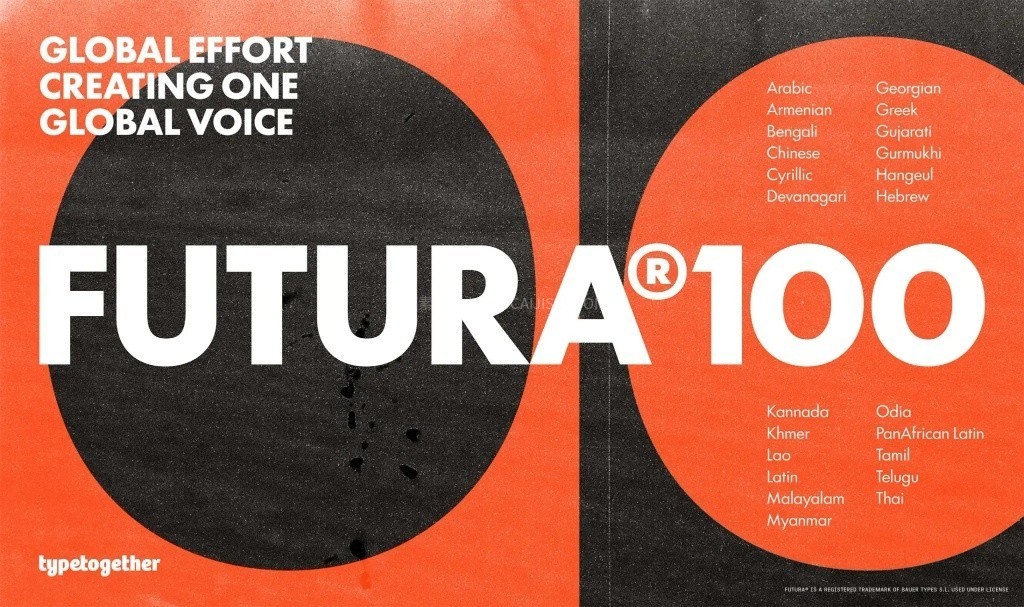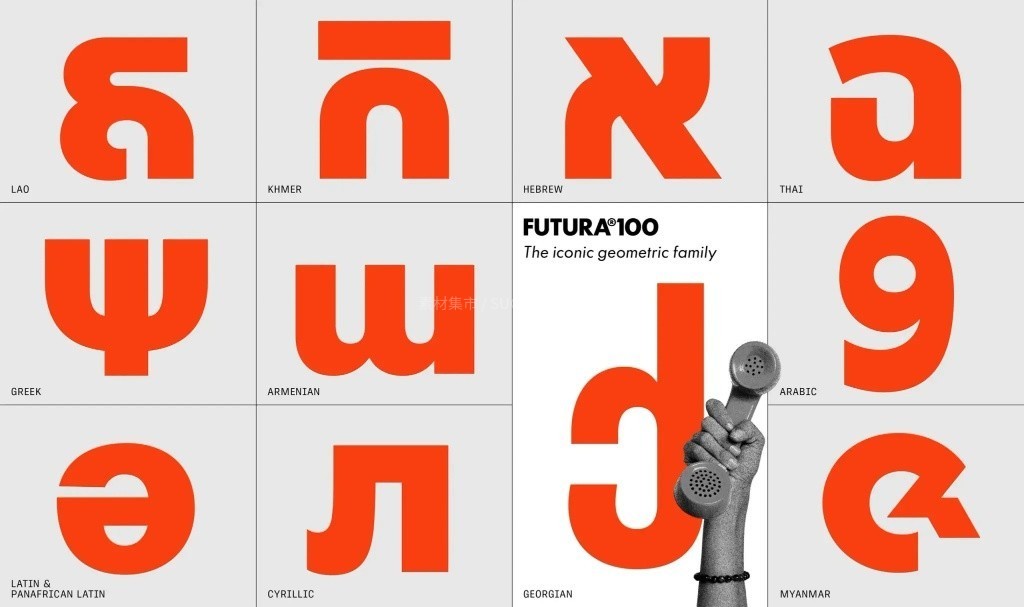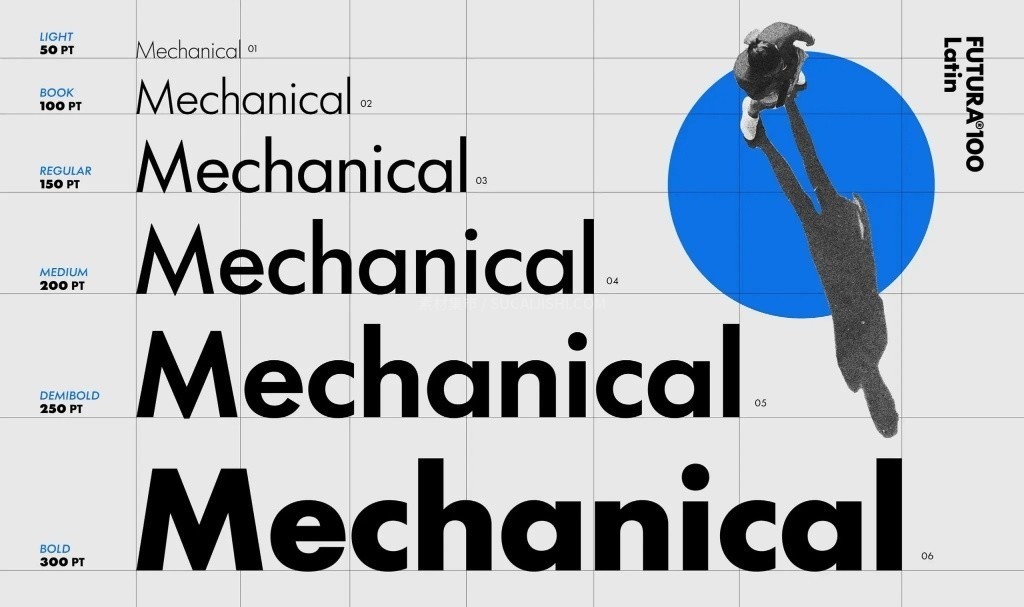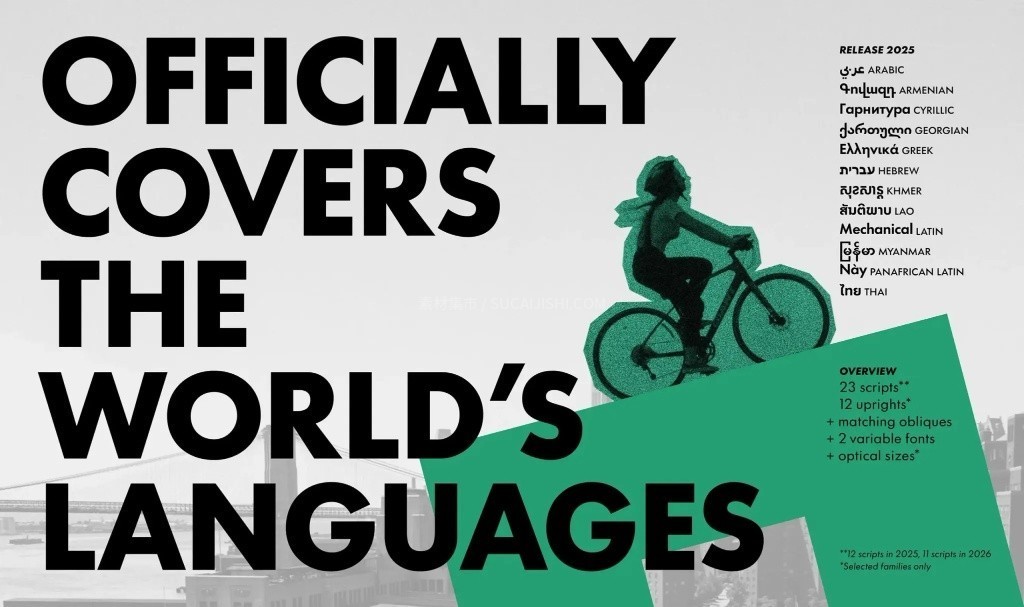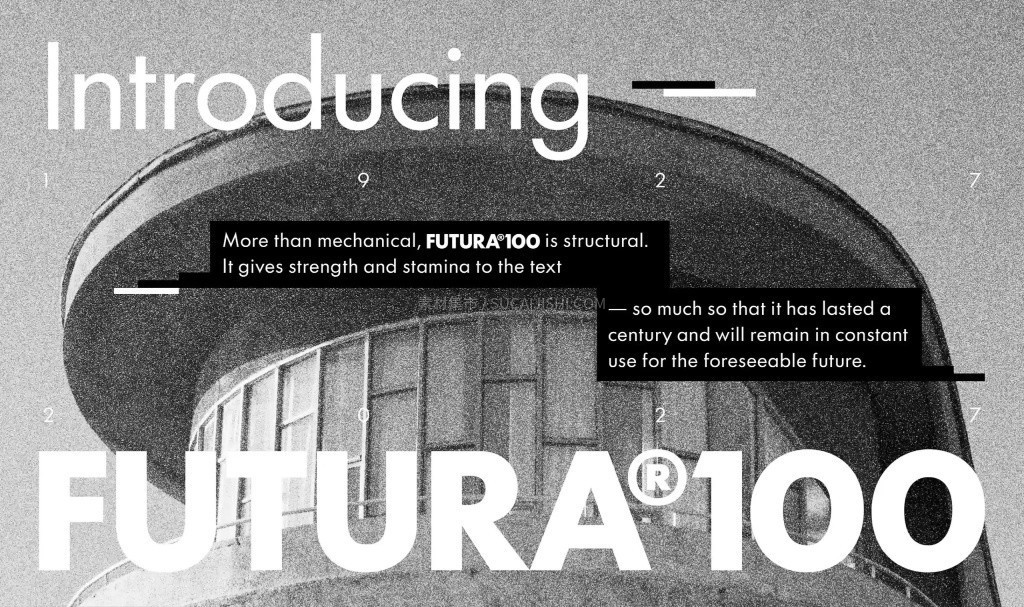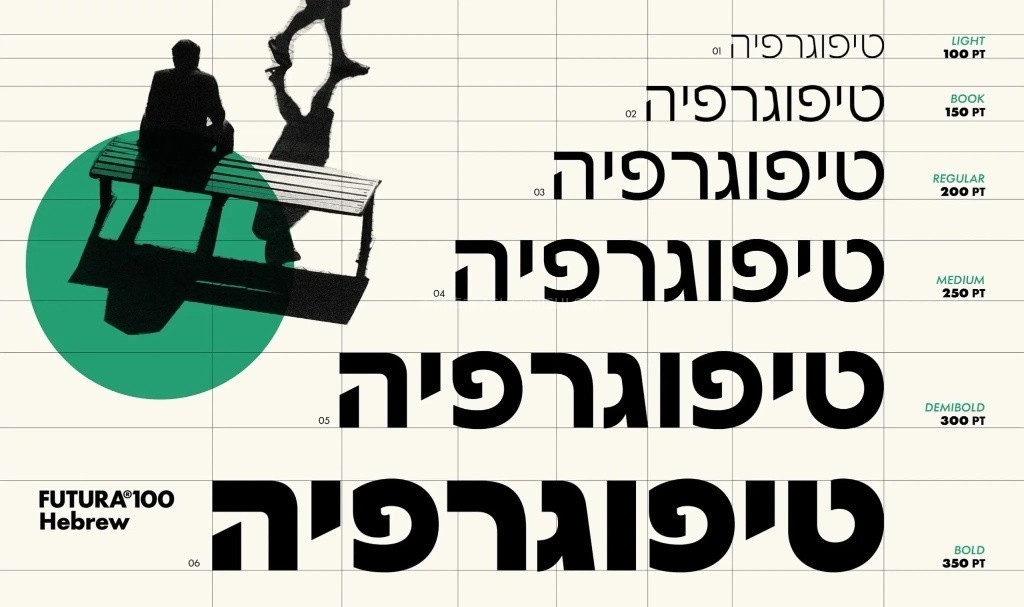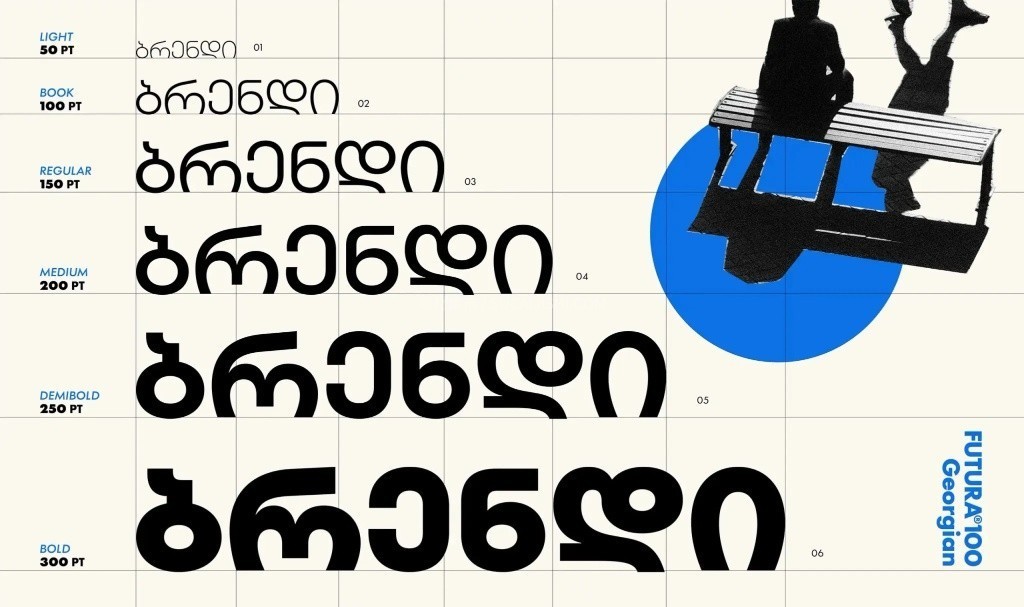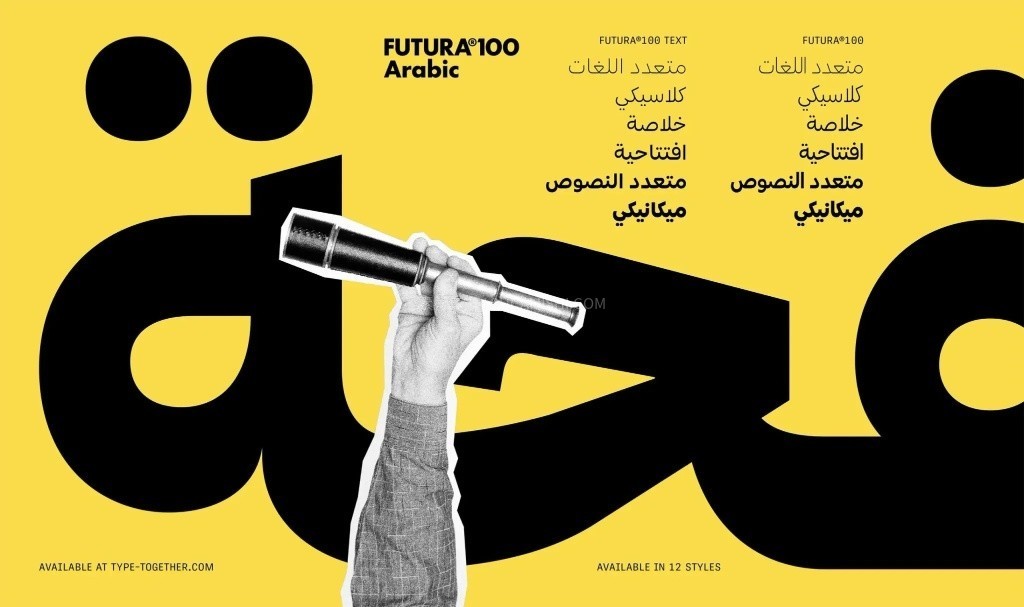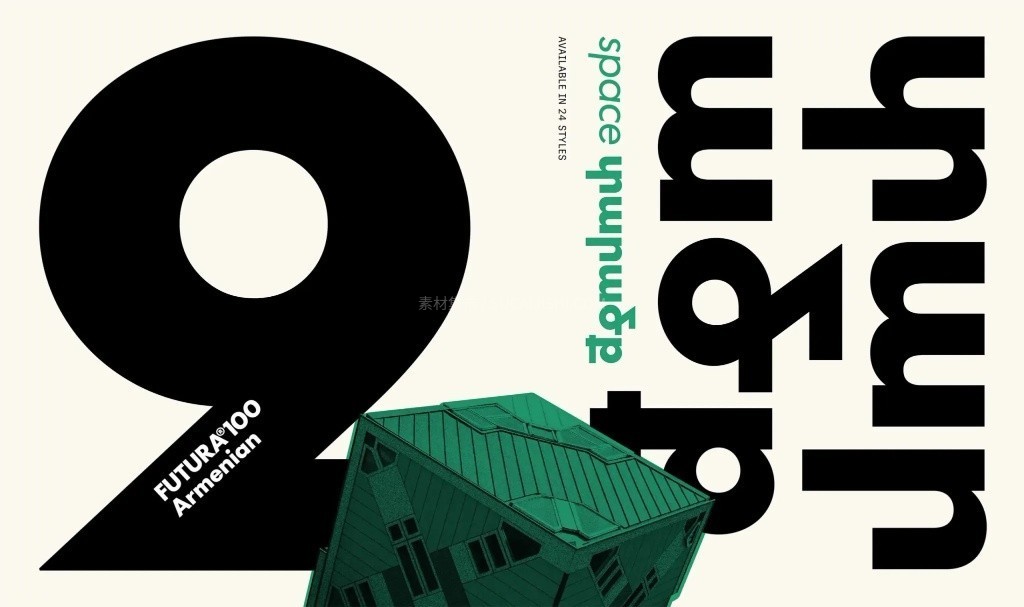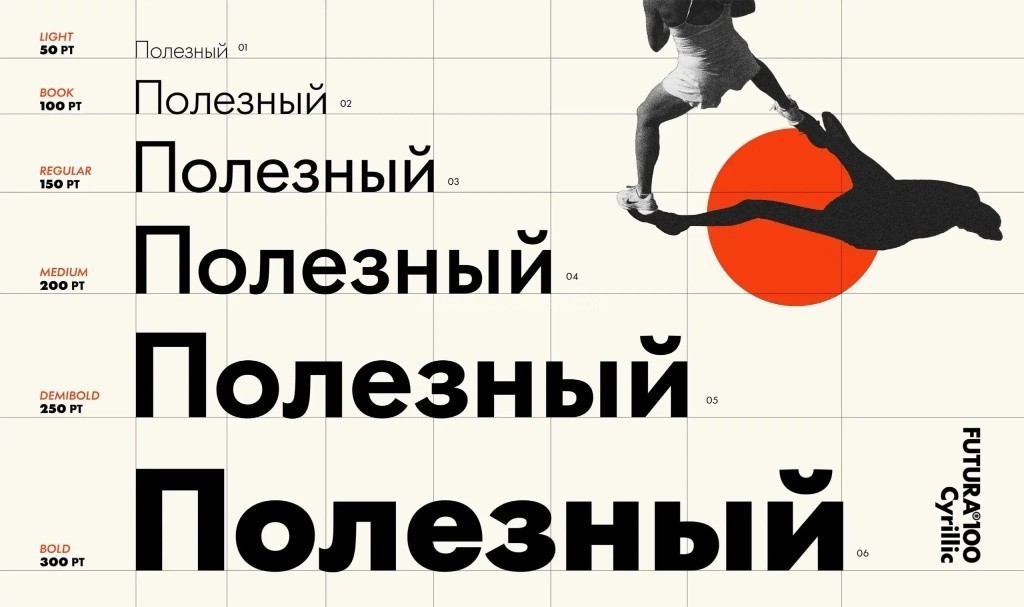
Futura 100 经典几何多语言字体库
这是一款备受大家喜爱的标志性几何字体!它拥有干净流畅的线条和稳重大气的视觉效果,能帮你轻松打造出极具高级感和吸引力的品牌形象。最特别的是,这款字体真正做到了“全球通用”,支持阿拉伯语、希腊语、泰语等 12 种不同的文字体系,能轻松搞定绝大多数国家的语言排版需求。套装内包含 12 种丰富的样式选择,以及可以灵活调节的字体文件,无论你是在做跨国大项目还是日常精美排版,这套字库都能完美适配,让你的设计既有历史底蕴又充满国际范儿!
Futura 100 经典几何多语言字体库